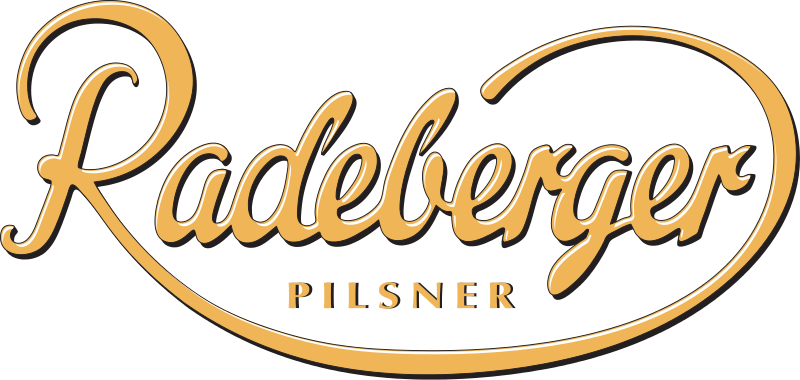
Radeberger Bier Schriftart
Die Exmouth sieht dem Beispiel schon recht ähnlich. Allerdings vermute ich, dass das Logo Handarbeit eines Designers ist und nicht auf einer Satzschriftart basiert.
Zuerst mal ist die Exmouth eine kalligrafische Schönschrift, aber der Schriftzug mehr ein traditionelles, formales Script. Die drei kleinen e deuten aber auf die Verwendung und/oder Abbänderung einer Vorlage hin. Das kleine r ist auch ein Hinweis auf eine eher deutsche Herkunft, bei der Emouth hat man das typische r aus dem englischsprachigen Raum. Meine Unterlagen greifen da aber ins Leere ...
Mein Tipp: Die „Vorlage“ war mit großer Wahrscheinlichkeit ein formales Script aus Deutschland oder dem deutschsprachigen Raum oder ggf. der näheren Nachbarschaft aus dem letzten Jahrhundert, möglicherweise der ersten Hälfte dieses Jahrhunderts.
Ich denke da an so was wie die „Forelle“ von Erich Mollowitz aus dem Jahr 1936: